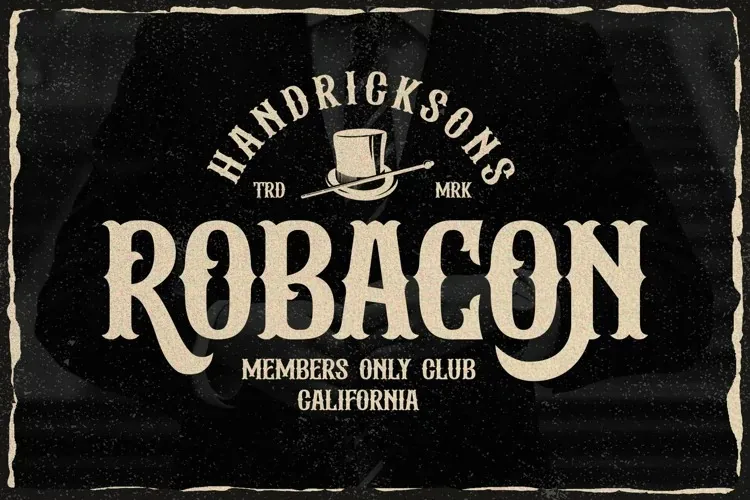
Albertson Font – Fonte Grátis
Albertson Font
A font Albertson é uma exuberante tipografia vintage criada à mão para inspirar no estilo de cartazes clássicos modernos. Este tipo de fonte oferece a oportunidade perfeita para designers que desejam incorporar um toque clássico em suas criações, como logotipos, marcas, embalagens, sinalizações e muito mais. Com seu estilo único e vibrante, Albertson traz uma atmosfera vintage ao design moderno sem perder a modernidade necessária para ser aplicável em várias situações de comunicação visual. Engane-se se pensasse que Albertson era apenas um tipo clássico: ele também pode ajudar você a criar soluções criativas e únicas, adaptando seu design para uma perspectiva contemporânea. Descubra o charme desta fonte em sua próxima peça de arte visual.